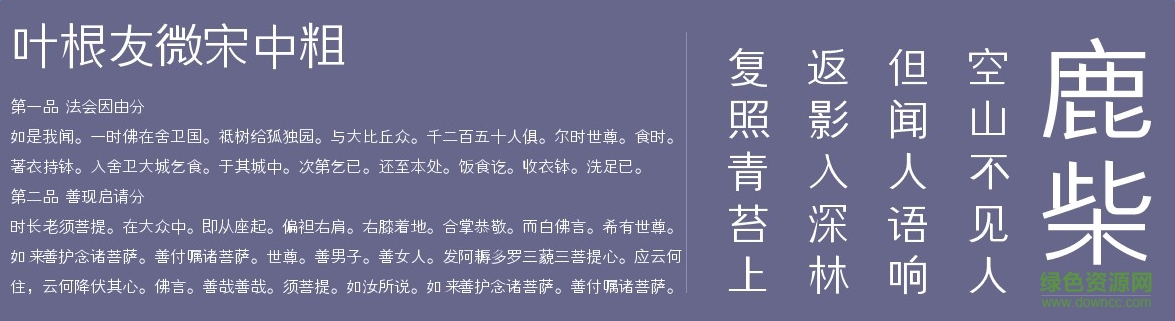
葉根友微宋中粗字體是一款由知名書法家葉根友創(chuàng)造的字體,比劃圓潤,適用于廣告、藝術(shù)設(shè)計(jì),海報(bào)設(shè)計(jì)等方面,有需要的朋友們不要錯(cuò)過了。歡迎大家來綠色資源網(wǎng)踴躍下載哦!
葉根友微宋中粗字體是一款表達(dá)圓潤思想的字體,取自中國東方圓潤之美的韻律,吸取中國漢字獨(dú)有的結(jié)構(gòu)表現(xiàn)特質(zhì),雍容華貴的體現(xiàn)了書法字體的美好一面。
葉根友微宋中粗字體,用途廣泛,是葉根友先生的印刷字體,適合場合很多,字體看起來比較正式。各位字體收藏者可以來看看。